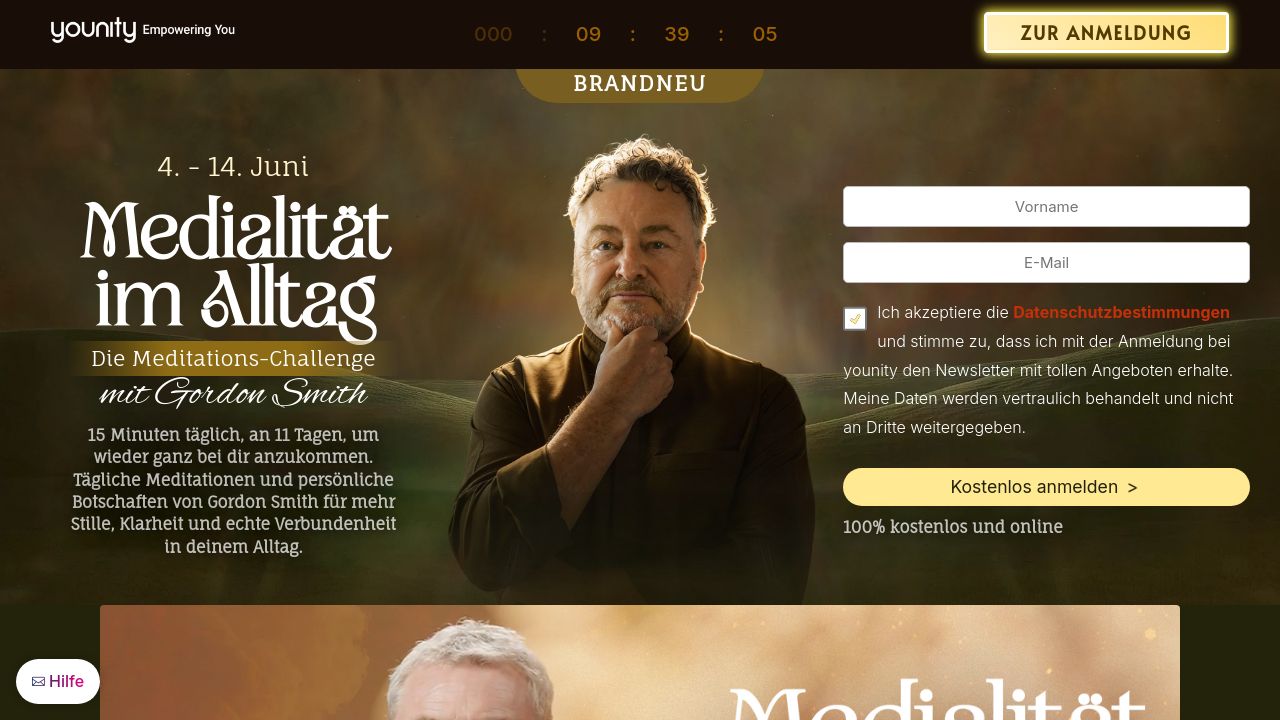
Medialitaet은(는) 어떤 폰트를 사용하나요?
Medialitaet.academy은(는) 기본 폰트로 Inter, Alata, Raflesia, Montserrat 및 Amiri을(를) 사용합니다. Arial, Helvetica, Georgia 및 Times New Roman은(는) 대체 폰트로 지정되어 있습니다. 폰트 16개 감지, 마지막 확인: 2026년 6월 3일.
medialitaet.academy는 명상과 내면 탐구에 중점을 둔 사이트로, 사용자들에게 편안함과 친근감을 제공합니다. Arial과 Inter 같은 시스템 및 커스텀 글꼴은 안정적인 기반을 제공하며, Montserrat와 DM Serif Display는 세련된 느낌을 더해줍니다. Quicksand와 Amiri 같은 다채로운 글꼴은 사이트의 따뜻한 분위기를 강조합니다. 이 모든 글꼴은 명상이 주는 고요함과 내면의 평화를 시각적으로 표현합니다.
Medialitaet.academy의 폰트에 대한 자주 묻는 질문
Medialitaet.academy은(는) 어떤 폰트를 사용하나요?
Medialitaet.academy은(는) 기본 폰트로 Inter, Alata, Raflesia, Montserrat 및 Amiri을(를) 사용합니다. Arial, Helvetica, Georgia 및 Times New Roman은(는) 대체 폰트로 지정되어 있습니다. 폰트 16개 감지, 마지막 확인: 2026년 6월 3일.
medialitaet.academy에서 어떤 글꼴을 사용하나요?
medialitaet.academy는 Arial, Inter, Montserrat, DM Serif Display, Quicksand, Amiri 등의 다양한 글꼴을 사용합니다.
이 글꼴들은 다른 글꼴과 어떻게 비교되나요?
Inter와 Montserrat는 현대적인 디자인에 적합하며, 가독성이 뛰어나고 다양한 스타일과 두께를 제공합니다. DM Serif Display는 클래식한 느낌을 주어 조화롭게 사용됩니다.
이 사이트의 글꼴 스타일과 두께는 무엇이 있나요?
medialitaet.academy는 다양한 두께의 Montserrat(100-900), Quicksand(300), Amiri(400, 700) 등 다채로운 스타일을 사용하여 시각적인 다양성을 제공합니다.